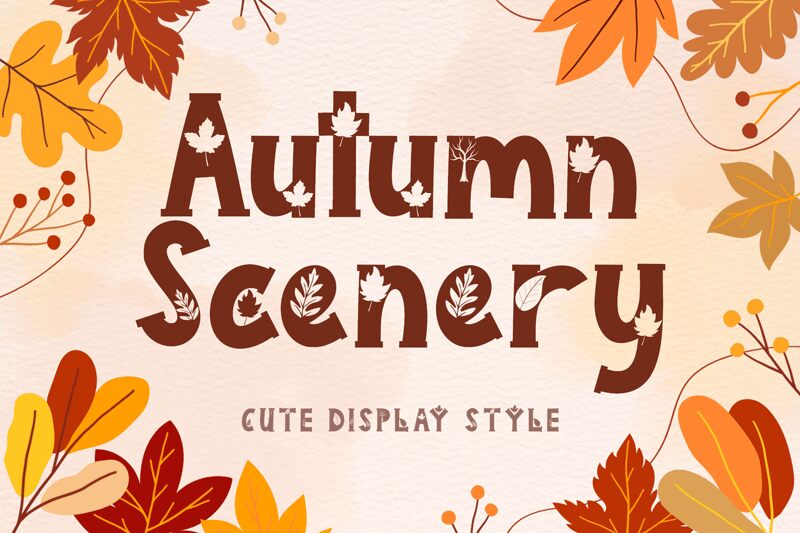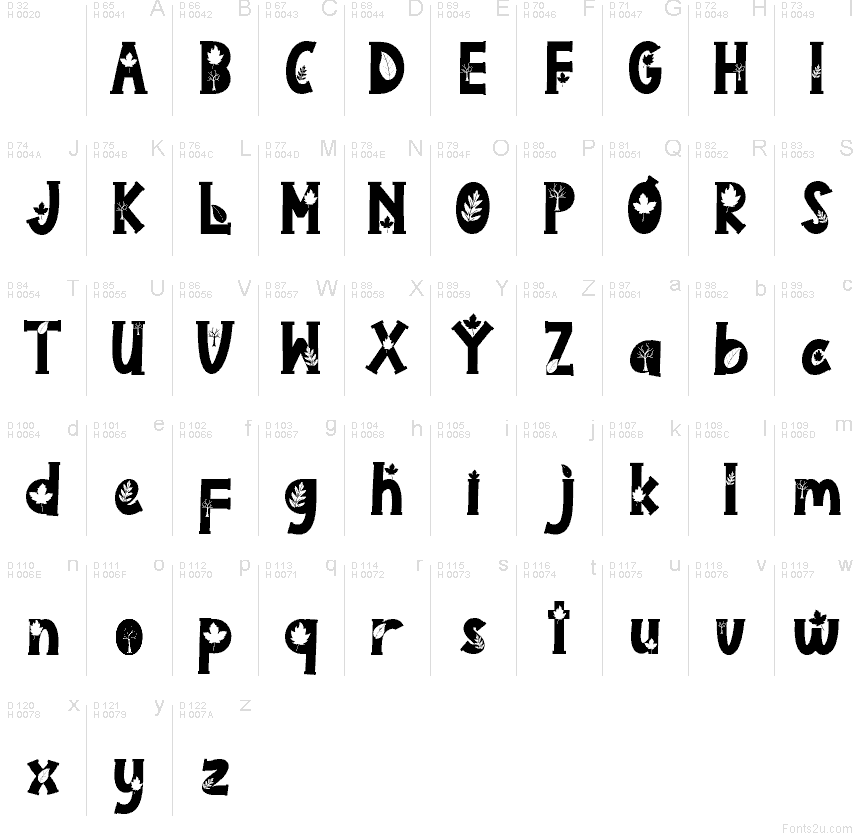
Autumn Scenery
"Autumn Scenery" de Yoga Letter est une police d'affichage gratuite sur le thème de l'automne, agrémentée de détails découpés et d'accents de feuilles et de branches. Ses caractères aux formes larges et robustes intègrent de petits motifs saisonniers dans les majuscules, apportant une esthétique artisanale évoquant la saison des récoltes, sans pour autant saturer le design.
"Autumn Scenery" est une police gratuite idéale pour vos affiches d'automne, flyers saisonniers, cartes de vœux, enseignes de magasin, emballages artisanaux et logos inspirés par la nature. Ses détails végétaux en font un choix parfait pour ajouter une touche automnale claire, que ce soit au-dessus d'un titre, sur une étiquette ou dans une mise en page rustique.